ps艺术字体可以使结构错落有致,字体大而不臃,在各种杂志和印刷品以及个人的签名都有着广泛的应用,经过psd后的字体结构端庄,一些字体丰满圆润,一些字体骨络分明,且它们的风格具有独特性,那么ps艺术字体主要用于哪些行业呢?它们有哪些作用呢?
ps艺术字体的例子不在少数,运动品牌,一个是鸿星尔克,一个是安踏,红星尔克的阳光让人感情非常舒适、非常闲逸,一个手写艺术字,给人感觉非常强烈、非常有力量感和运动气息的一个艺术字,它们所表现出来的感觉是完全不同的,当我们设计这种slogan的时候,要充分考虑到品牌所要表达的感觉和概念,义启字库建议用最合适的元素去表现,才能够充分表达品牌倾诉的内容,能够让消费者了解到要干什么。
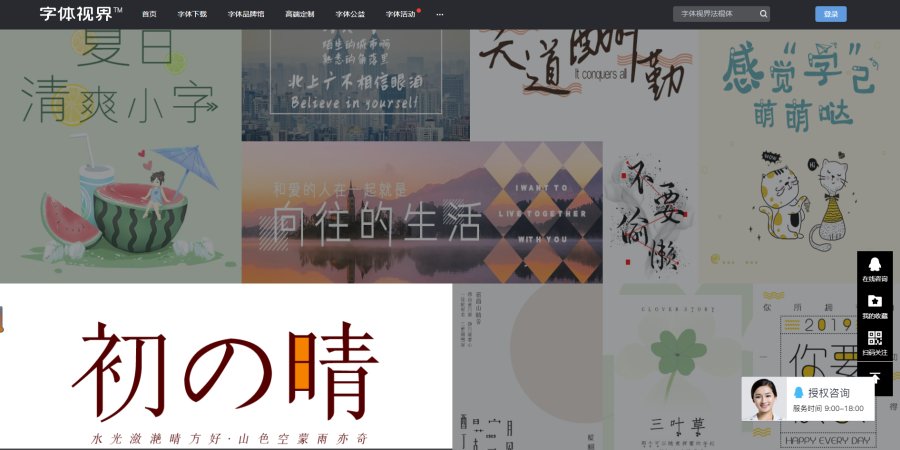
那么怎样去利用一种已知的字库的宋体进行设计变化或者创意字体提升,可进行一个简化化的处理,如果再仔细的辨识一下,要明确表现出艺术字的特征,证明它并不是常规的字体,所以如果想要改造一个宋体,应该让它呈现出不同的感觉,如果做的改变非常细微,让别人看不出来,那我们ps艺术字体灵感相当于归零,因为你的工作没有达到目标,所要呈现出来的设计感不会也发现。
在义启字库的字体中,大多用作各行业的装饰和美化,广告设计中应用量更大,它既符合字体结构指向性,又有着独特的设计规律,独具匠心的艺术字独具魅力。